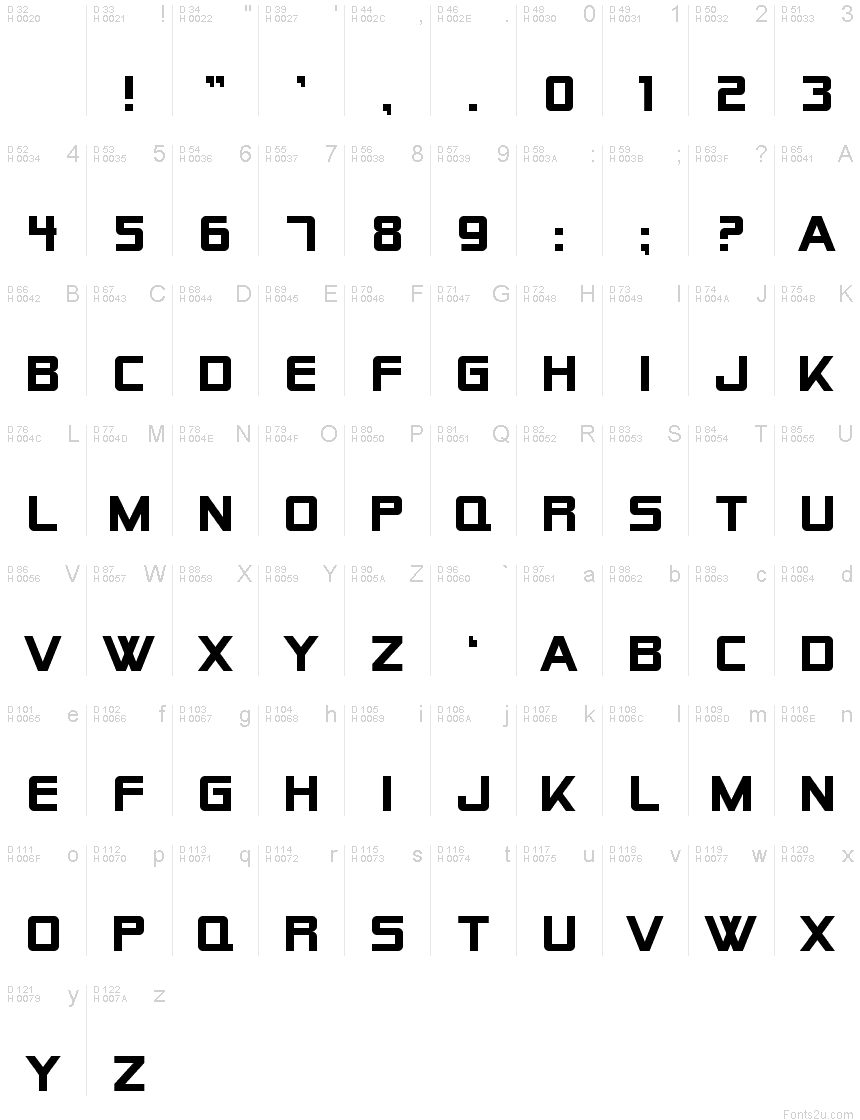
SF Alien Encounters Solid von ShyFoundry ist eine kostenlose Sci-Fi-Display-Schrift für Großbuchstaben, die durch ihre stumpfen, modularen Formen und einen coolen Retro-Futurismus-Vibe besticht. Die Buchstaben wirken wie aus massiven geometrischen Blöcken gemeißelt: Eine Mischung aus eckigen Kanten, breiten horizontalen Schnitten und scharfen, dreieckigen Akzenten lässt das gesamte Set wie die Beschilderung eines visionären Raumschiffs aus vergangenen Jahrzehnten wirken.
Sie passt perfekt zu Gaming-Logos, Filmpostern, Comic-Covern, Album-Artworks oder Titelkarten, bei denen kurze Begriffe diese synthetische, außerweltliche Stimmung brauchen. Als Gratis-Font eignet sie sich zudem hervorragend für Monogramme oder große Initialen, da die Buchstaben dank ihrer wuchtigen Präsenz und ungewöhnlichen Formgebung auch ohne zusätzliche Illustration sofort die Blicke auf sich ziehen.